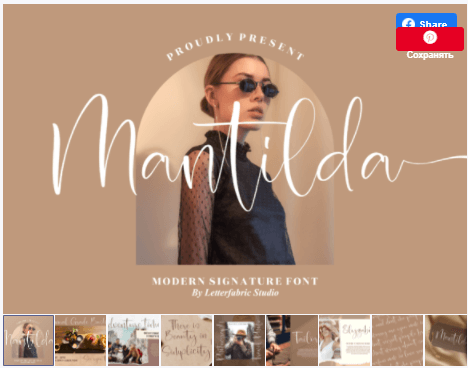
Mantilda Font
Mantilda — это стильный изысканный рукописный шрифт, излучающий изысканность и элегантность. Благодаря стильным альтернативам и лигатурам этот шрифт идеально подходит для любого проекта.